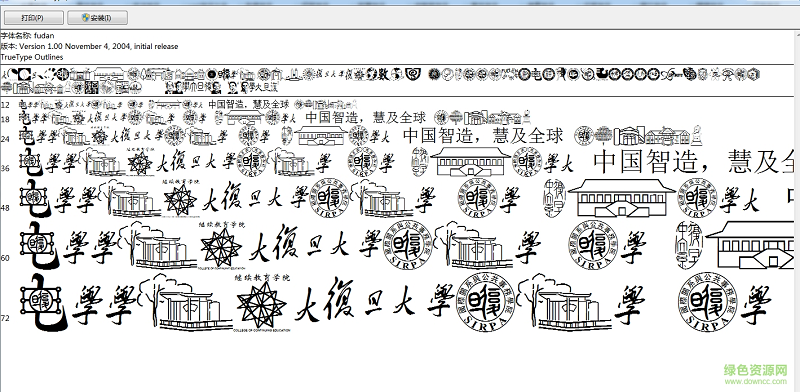
復(fù)旦字體是一款針對(duì)復(fù)旦大學(xué)而推出的一款藝術(shù)字體,字體帶有復(fù)旦?;?、標(biāo)志等,大學(xué)人文氣息相當(dāng)濃厚,特別適合學(xué)校相關(guān)設(shè)計(jì)領(lǐng)域!有興趣的朋友就來(lái)綠色資源網(wǎng)下載吧。